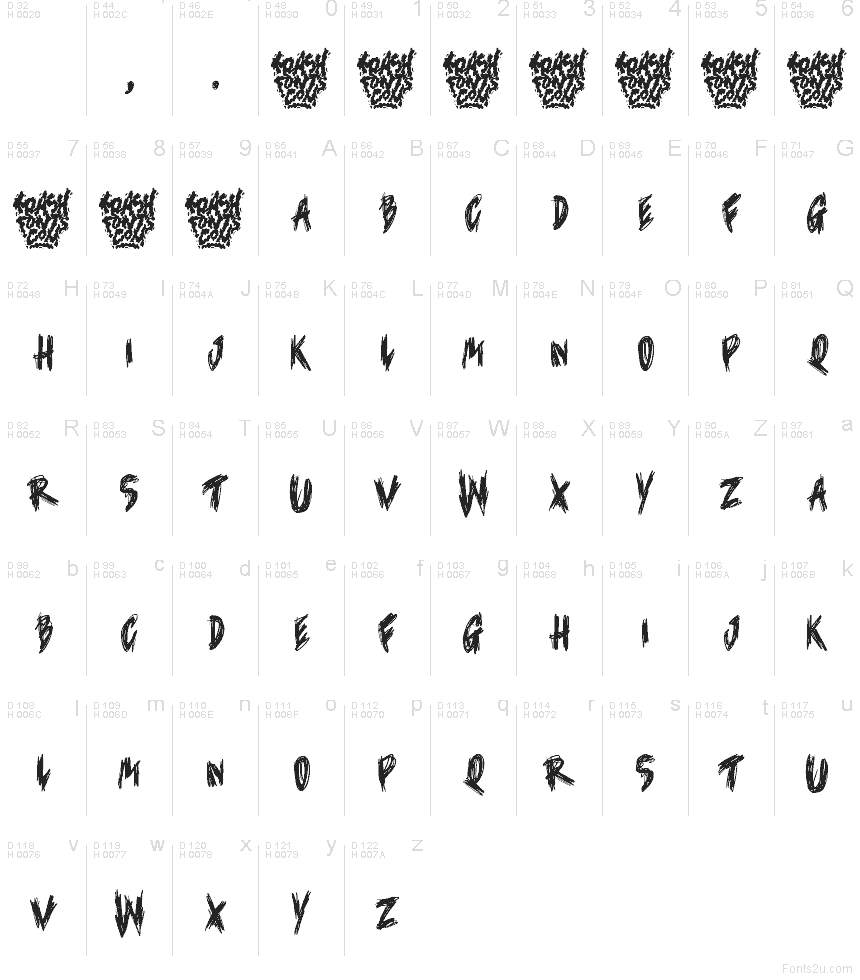
Trash Secret od Trash Fonts je bezplatné štětcové písmo s frenetickým, oškrábaným charakterem. Velká písmena vypadají, jako by byla nakreslená suchým fixem nebo štětcem – plno trhaných tahů, křížících se čar a nerovnoměrného přítlaku, což dodává písmu syrový nádech punkového fanzinu namísto úhledné typografie.
Hodí se na plakáty, obaly alb, streetwearovou grafiku, hororové titulky nebo rebelské nadpisy, kde chcete, aby písmena působila jako narychlo načmáraná. Jako bezplatný font funguje nejlépe v krátkých úderech – loga, monogramy, úvody kapitol nebo výrazné nápisy – protože drsné, švihnuté tvary dodávají atmosféru, ještě než si člověk přečte samotné slovo.